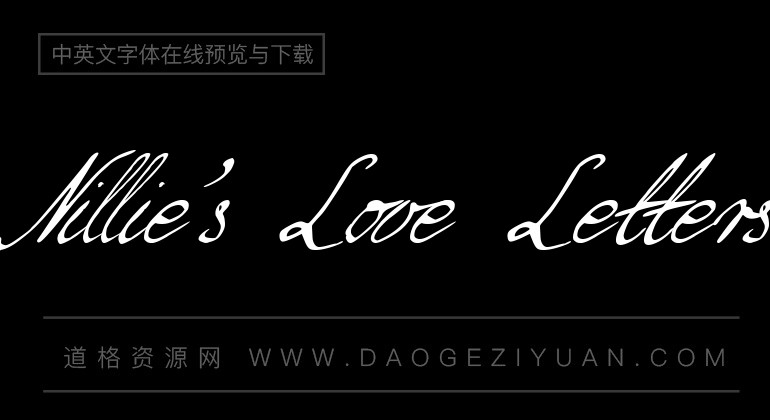
Nillie's Love Letters
Nillie's Love Letters字体是一款脆弱而优雅的手写字体,它具有细腻的笔画和柔和的色彩,可以用于制作浪漫的爱情信件和礼物标签。它的字体特点是细腻的笔画,柔和的色彩,以及一种优雅而脆弱的气质。它可以用于制作浪漫的爱情信件,礼物标签,婚礼邀请函,卡片,海报等。
Nillie's Love Letters是一款非常不错的手写艺术字体,具有很好的视觉感,适合于文化类的宣传设计、商业类品牌的广告和产品包装设计以及个性化文字排版等较多场景。